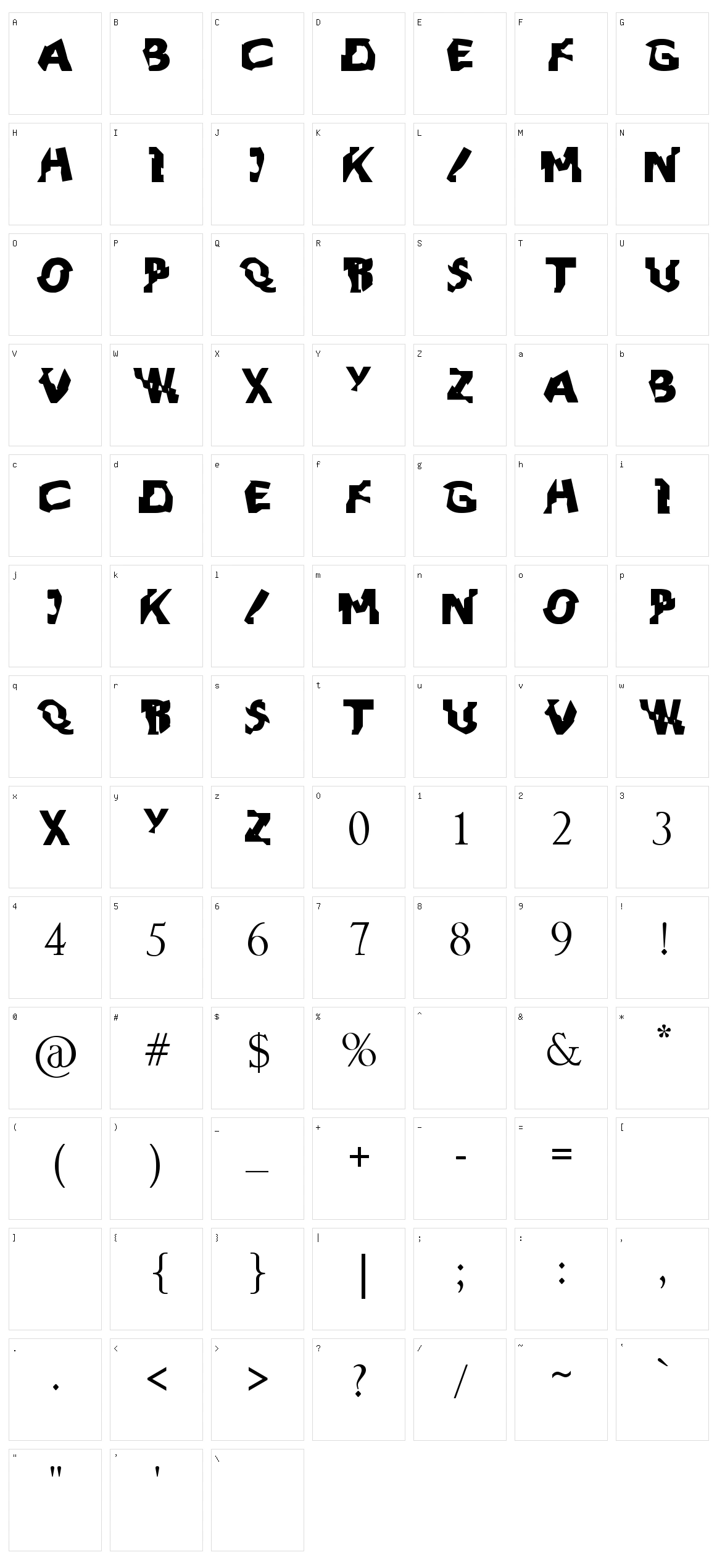
Es una primera version del tipo de fuente de la portada de ARTPOP
Preferentemente que se use en color rosa
Solo funciona en mayusculas
Los signos y numeros no pertenecen al tipo de letra